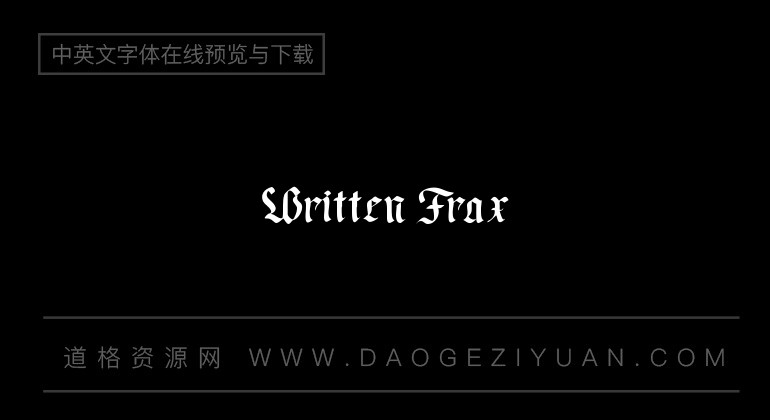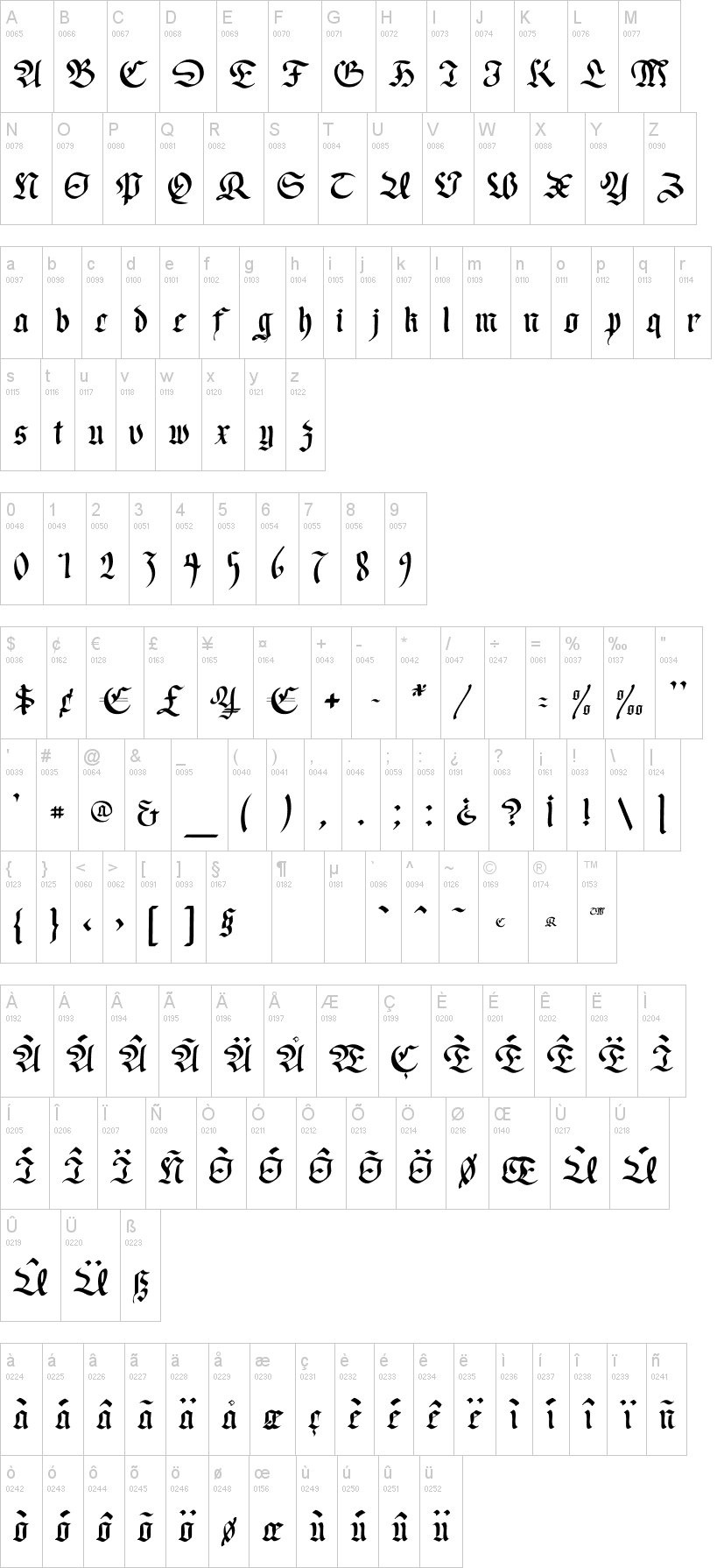
Written Frax
Written Frax 字体是一种手写风格的英文字体,由设计师 Fredrick Brennan 创作。这种字体的特点是模拟了手写字体的感觉,比较自然、随性,不太规整。它的使用场景比较广泛,可以用于卡通、漫画、广告等多种设计领域。 Written Frax 字体比较适合用于一些比较活泼、有趣、轻松的设计,因为它的视觉效果比较亲切、接近人们的书写风格。这种字体虽然不是特别正式,但是可以通过调整字体的大小、颜色、粗细来达到不同的视觉效果。 总的来说,Written Frax 字体是一种比较有趣、有活力的字体,适合用于一些需要表现轻松自然感觉的设计场景。
Written Frax是一款非常不错的手写艺术字体,具有很好的视觉感,适合于文化类的宣传设计、商业类品牌的广告和产品包装设计以及个性化文字排版等较多场景。
Written Frax字符映射图